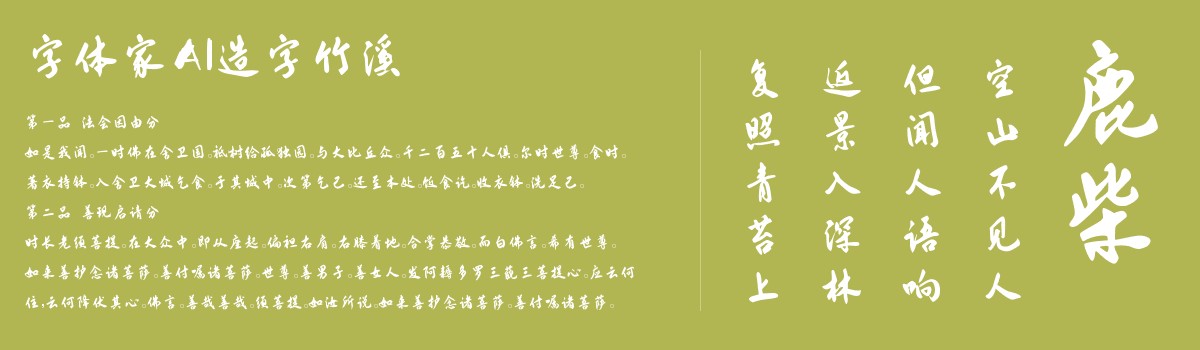
字体家AI造字竹溪
字体家AI造字竹溪是一款由字体家AI神笔造字生成的一款艺术字体,这款字体带着自然的手写温度,笔画似软毫笔轻书而就。起笔处如发丝轻拂,纤细中透着灵动;行笔渐显饱满,墨色仿佛随力度自然晕开;收笔时或轻挑带出,或略顿留余韵,提按变化藏着书写时的呼吸感。转折处无生硬棱角,皆以圆转过渡,像水流绕过石砾般柔和。笔画间偶有细若游丝的牵丝相连,不是刻意勾连,更似书写时笔尖自然带出的余痕。整体形态舒展却不散乱,每个笔画都有自己的呼吸空间,又相互呼应成整体,像春日柳枝,轻盈中透着韧劲。。比较适合用于艺术类装饰文字,海报、网页、广告设计,室内装饰,平面标题设计、食品包装、品牌标志等。